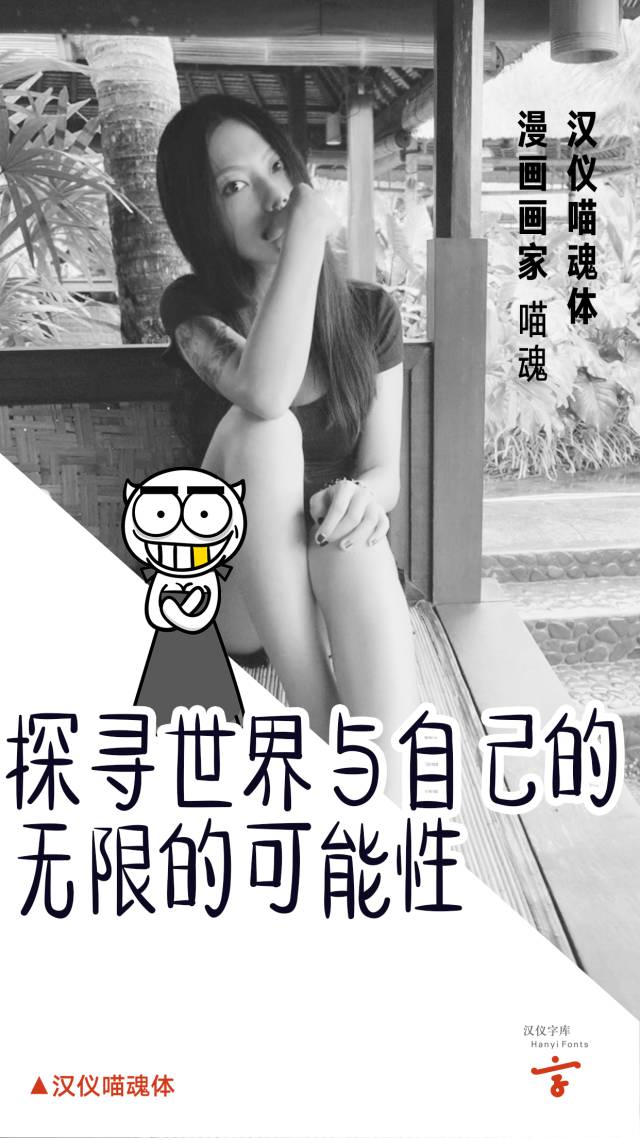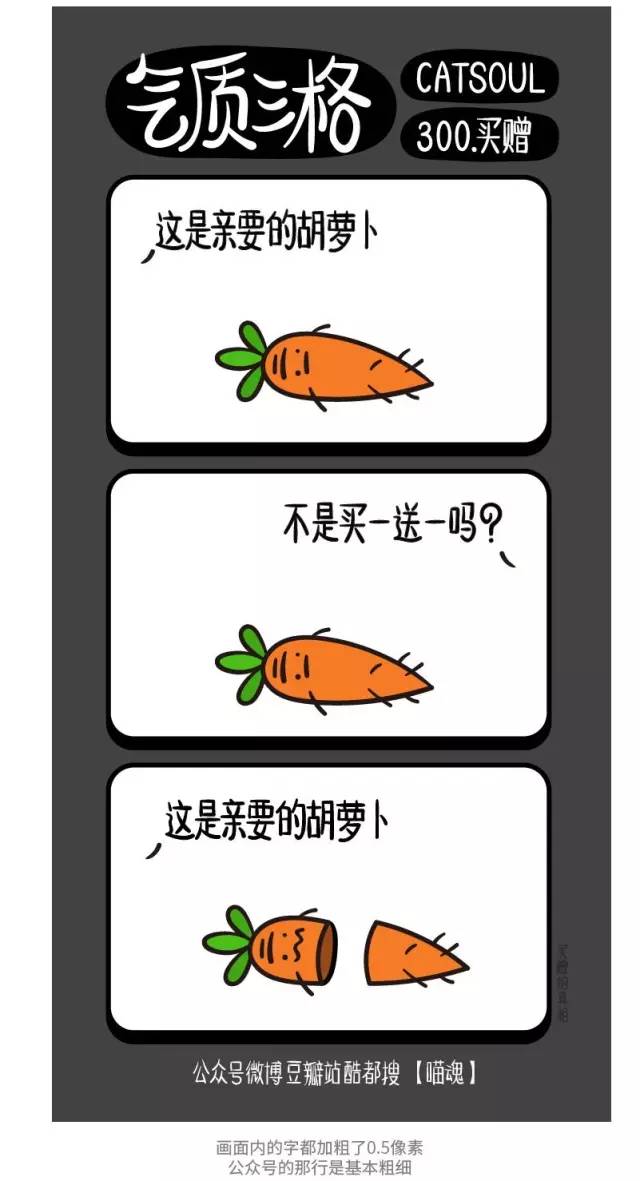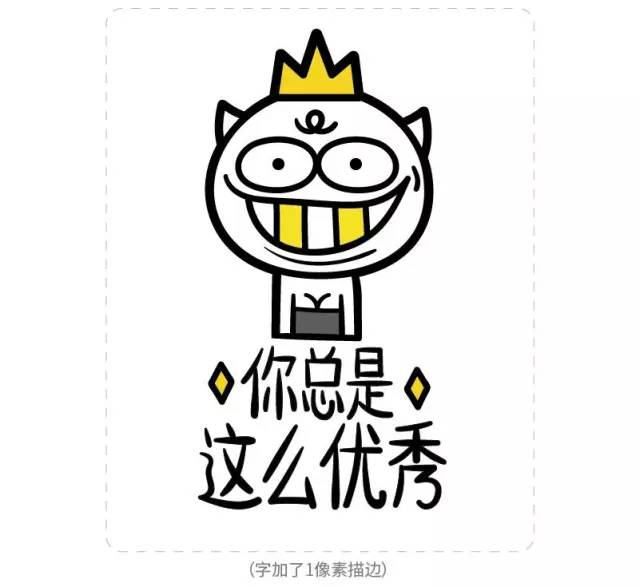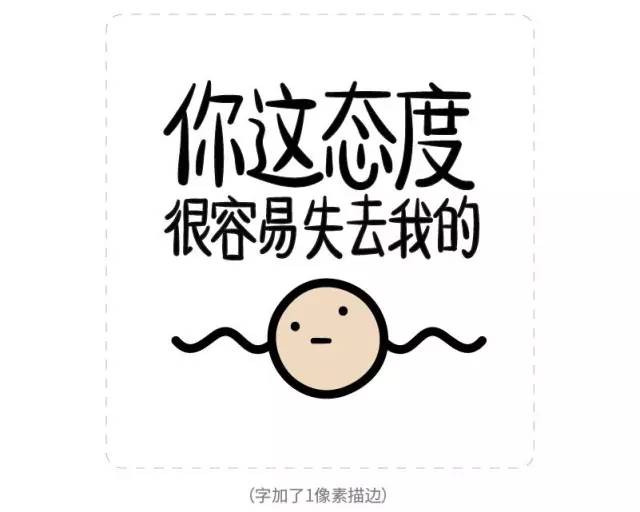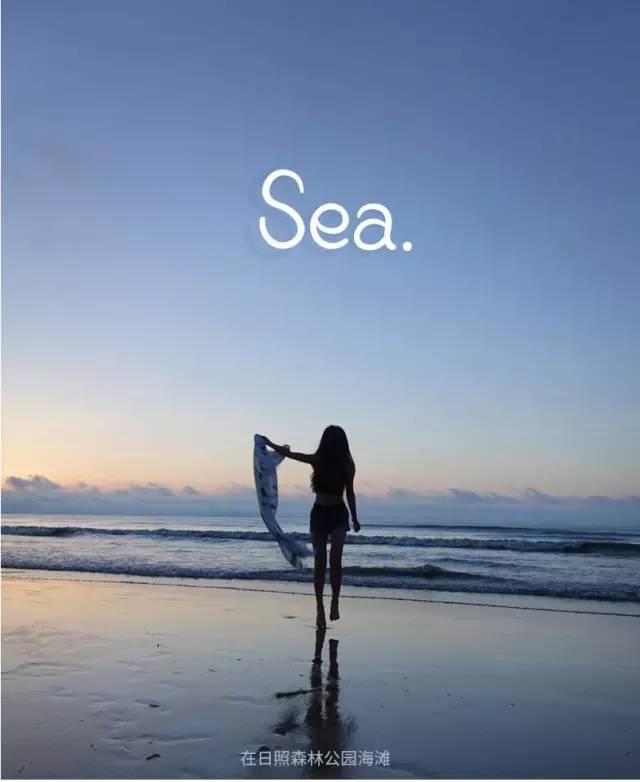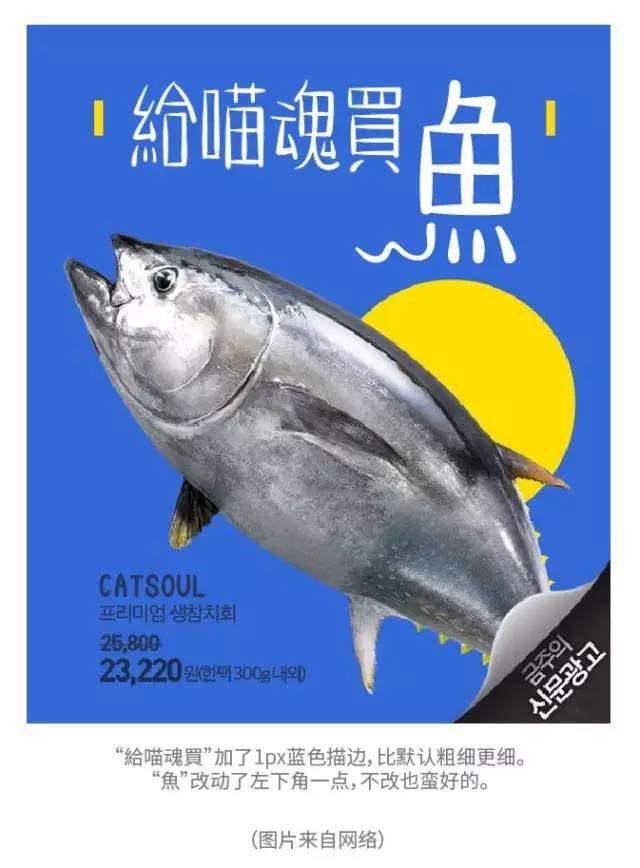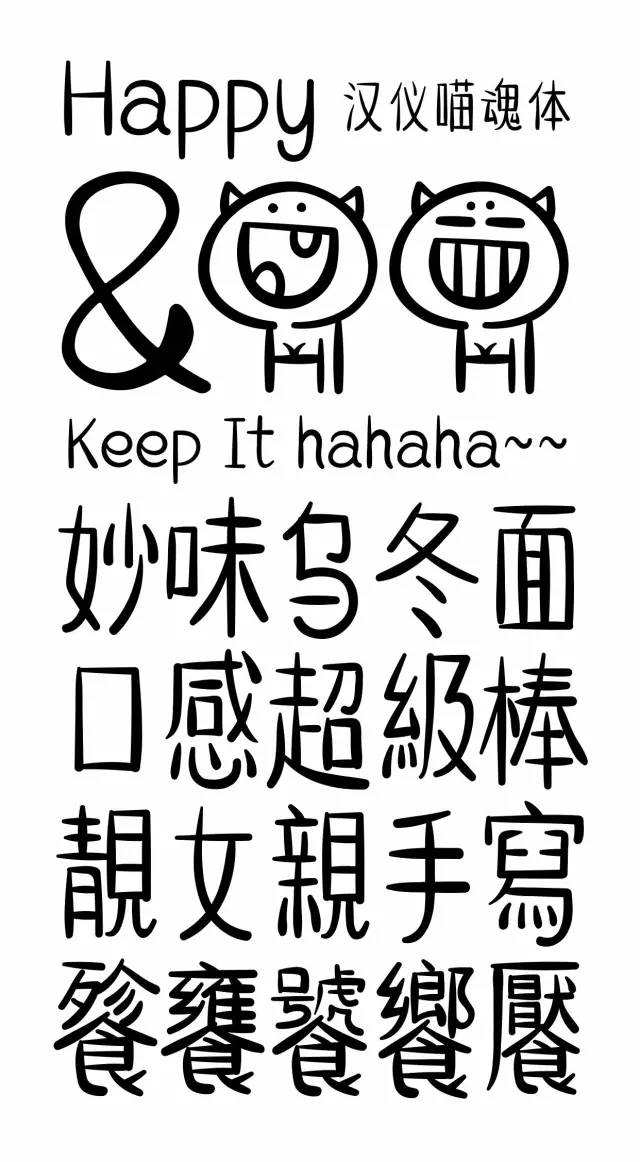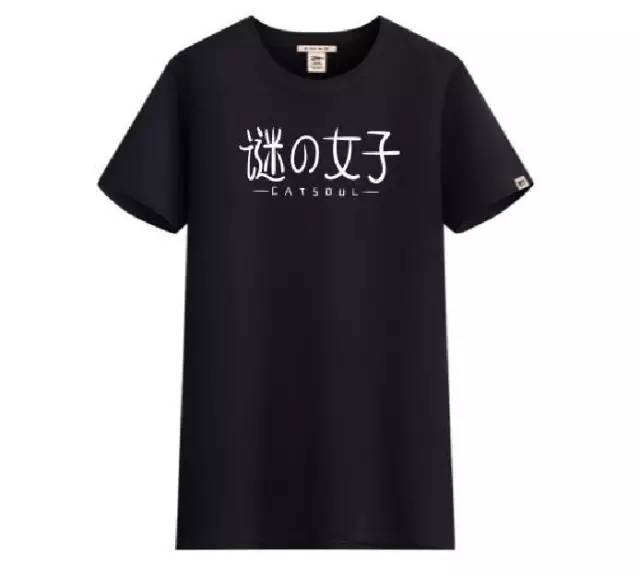
汉仪喵魂体介绍、案例,非常适合有调性的手写体
这是一套
标题,正文,单字都适用的
谜之调性手写体
汉仪喵魂体
字符集【W—中文简繁+网络常用字】
共9169汉字+14个表情
性格特征:柔软,俏皮,有趣,窈窕,轻盈
推荐用户年龄段:0-40
支持媒介:广告、标志、互联网,大标题,小段落文字排版
手写体作为字体的一种
因为能够充分表达人们的情感而被大家广泛地认可
漫画家喵魂也因其独特的调性
受到粉丝们的热情追捧
经历了几个月的奋战
一款如同乌冬面般Q弹的字体诞生了
而喵魂本人
也是地道的美女一只
那么
喵魂体有哪些特别之处呢?
特征一
柔软细腻有弹性,易开脑洞
比如一个给猪上酷刑的字
也念猪
但这个字的意思是……
再比如
这个是“龟”的繁体字龜
立刻就想起忍者神龟里面的拉斐尔
最后一个谜一样繁体的“傻”
看上去似乎比简体傻一万倍
特征二
附带14个奇妙表情
喵魂的表情目前对应上了emoji的一些国际通用表情的码位,
比如这个
谜样的喵魂表情打入了敌人内部
目前有14款
之后还会更新
线条和字体风格一致
大家可以打出来尽情玩耍
嵌入传统漫画
原谅喵大只画了一格
大家凑合感受一下
搭配条漫
据说出了字库解脱双手的感觉好极了
表情包必备好字体
柔软又友好
亲和力超群
中西文应用于平面设计
平面设计的世界里,
不管中文还是英文,
都带给画面良好的品质感
中文的表现,像个俏皮的宝宝
电商平台上保持柔软的姿态
产品实物
以下是傲娇的卖家秀(写手秀)
喵魂说
字库加标点接近一万字
我的极速是除了吃饭睡觉
一刻不停的写
一天最多300字
极速一天之后第二天就要最少崩溃半天(笑)
上半年因为出书有点拖延
到临交稿的两个月剩的有点多
我只好回老家闭关写
有一个半月的时间里
每天都&
从天亮写到天黑
从睁眼写到闭眼
微信朋友圈还合作什么的
啥也不管了不回了
特别的酸爽
坚持下来之后感觉耐力提升了一百倍
之后谁再说什么事儿忍不了抛不下
我就特别想说
你去抛下一切功名利禄社交合作
写俩月字库试试
之后什么矫情都没了
云淡风轻的
虽然我认为一定要写到最好才对得起用喵魂体的人
但根据我进步的速度
永远都写不到我认为的最好
这点特别的痛苦
所以大家看见哪个字儿特不好
自己改改粗细还是改改笔画的都行
我有时间一定会慢慢优化
——喵魂